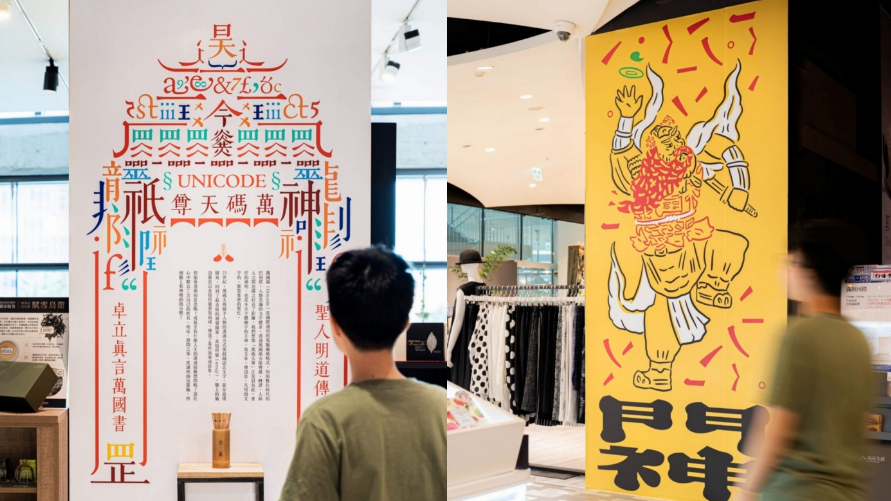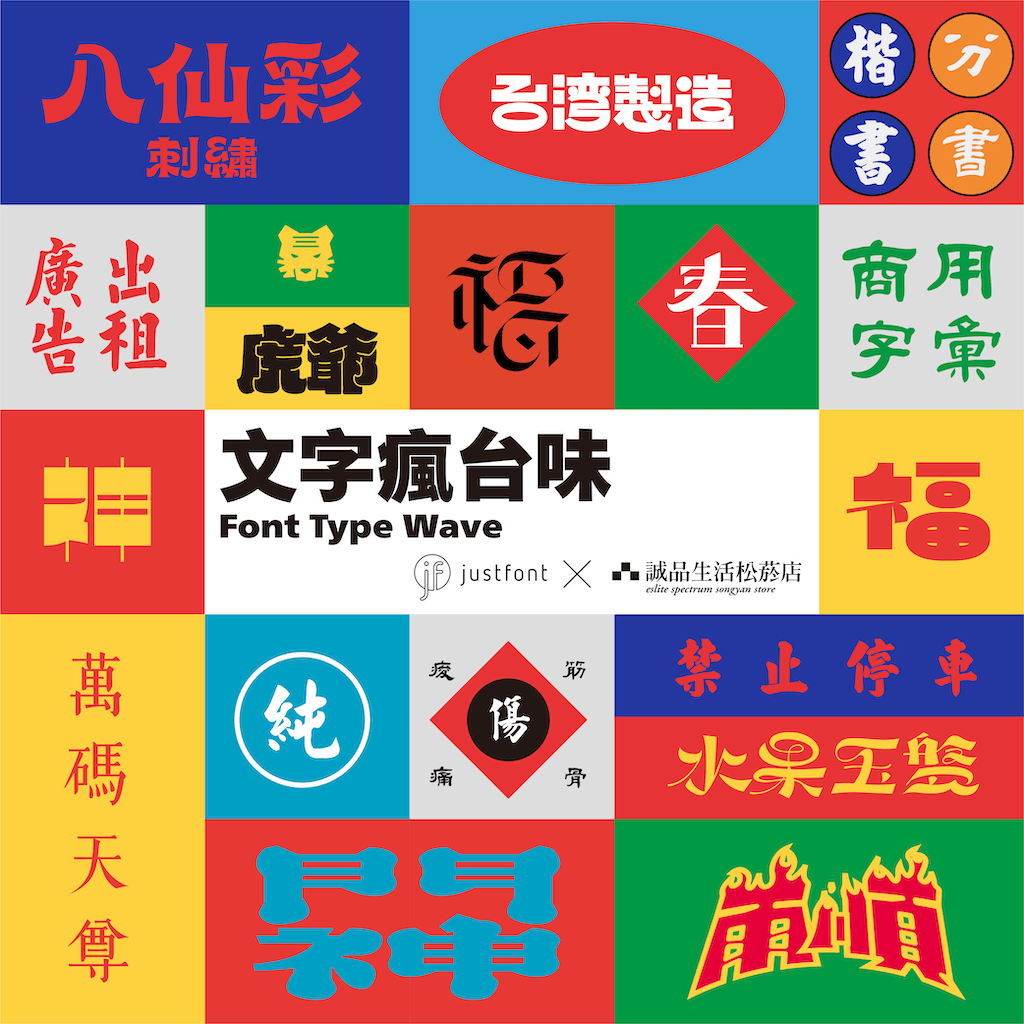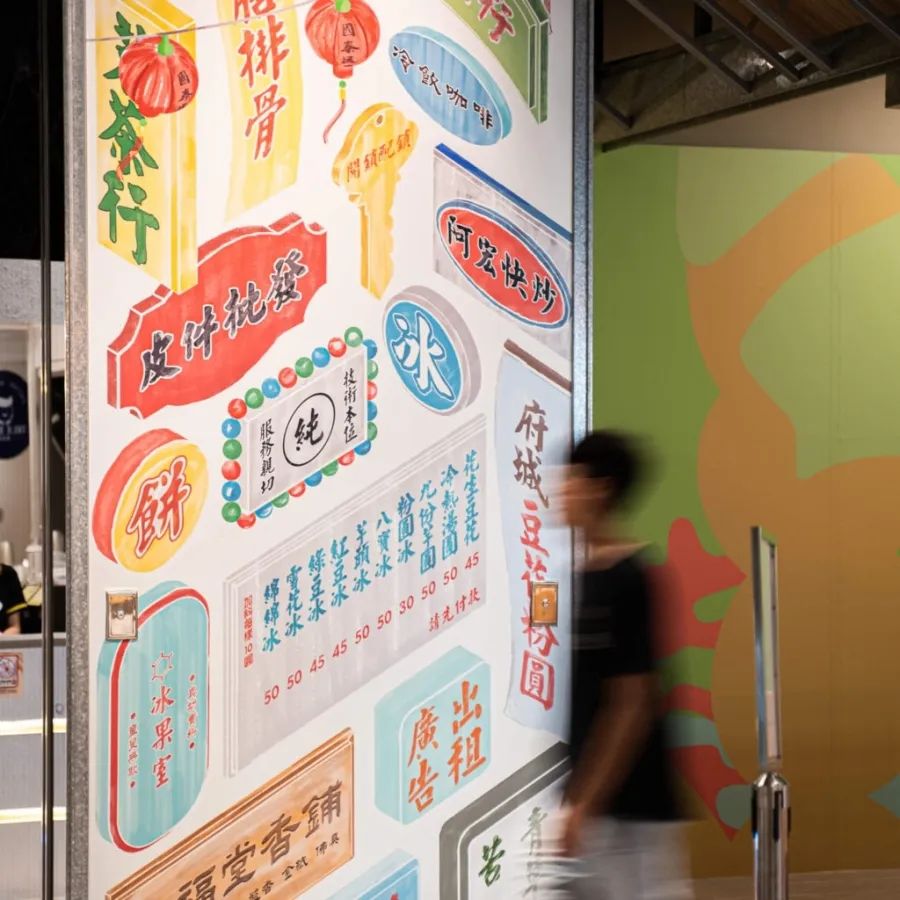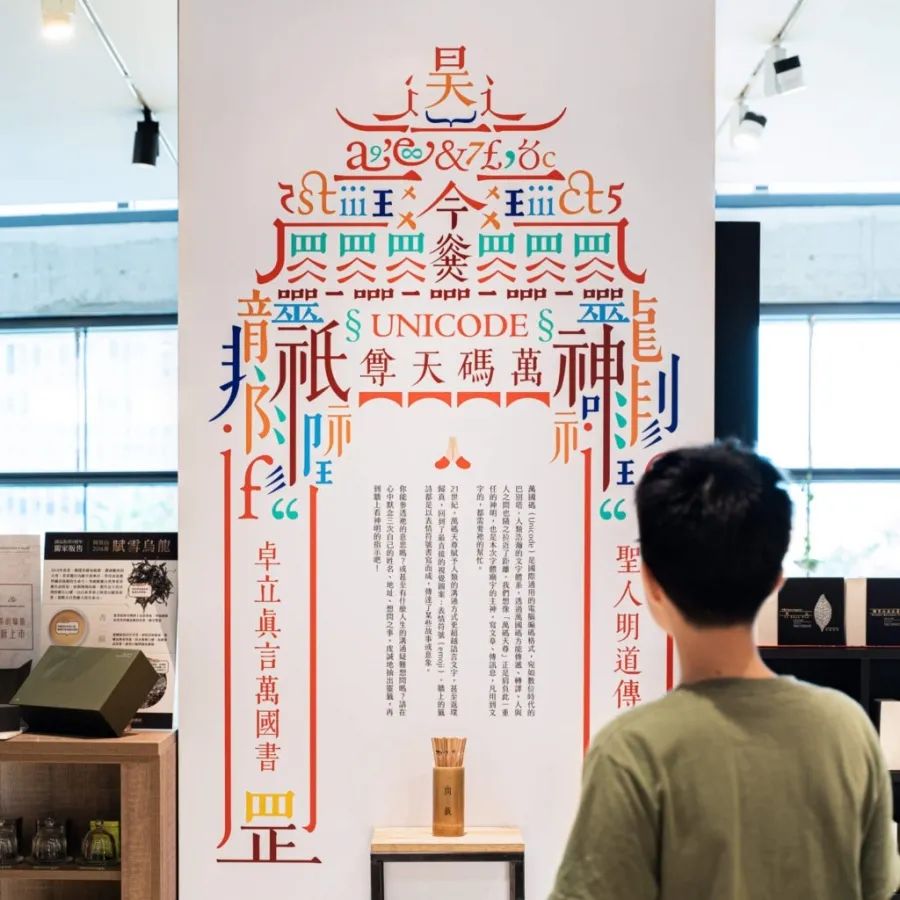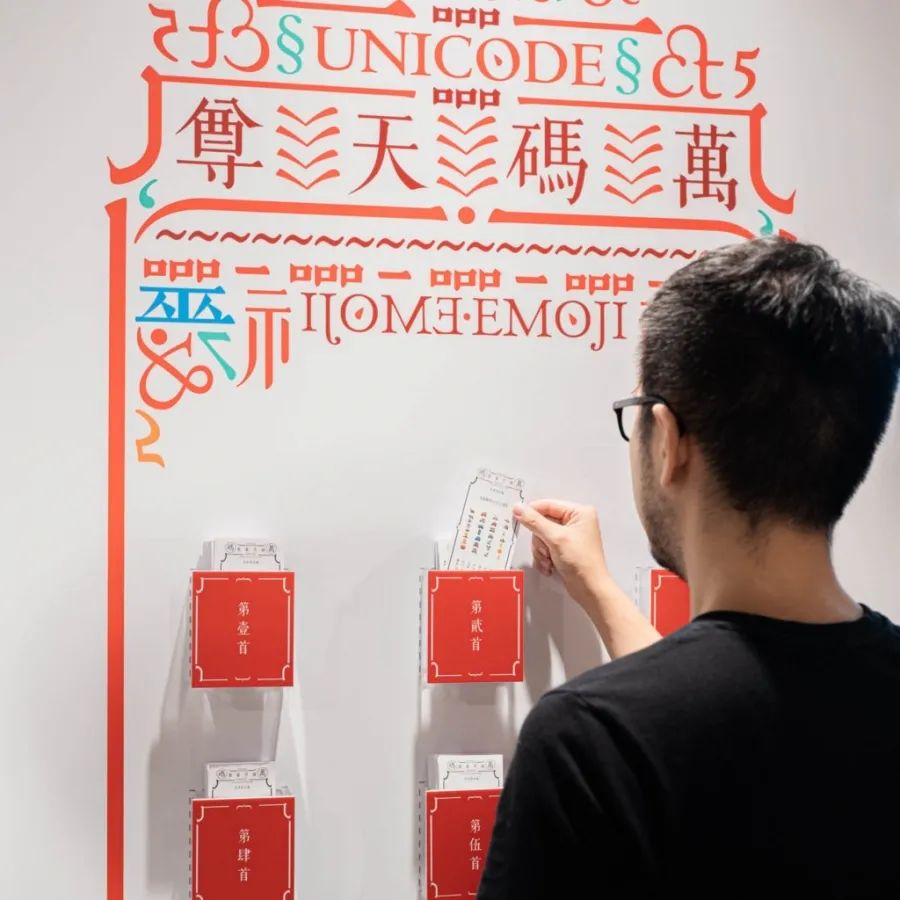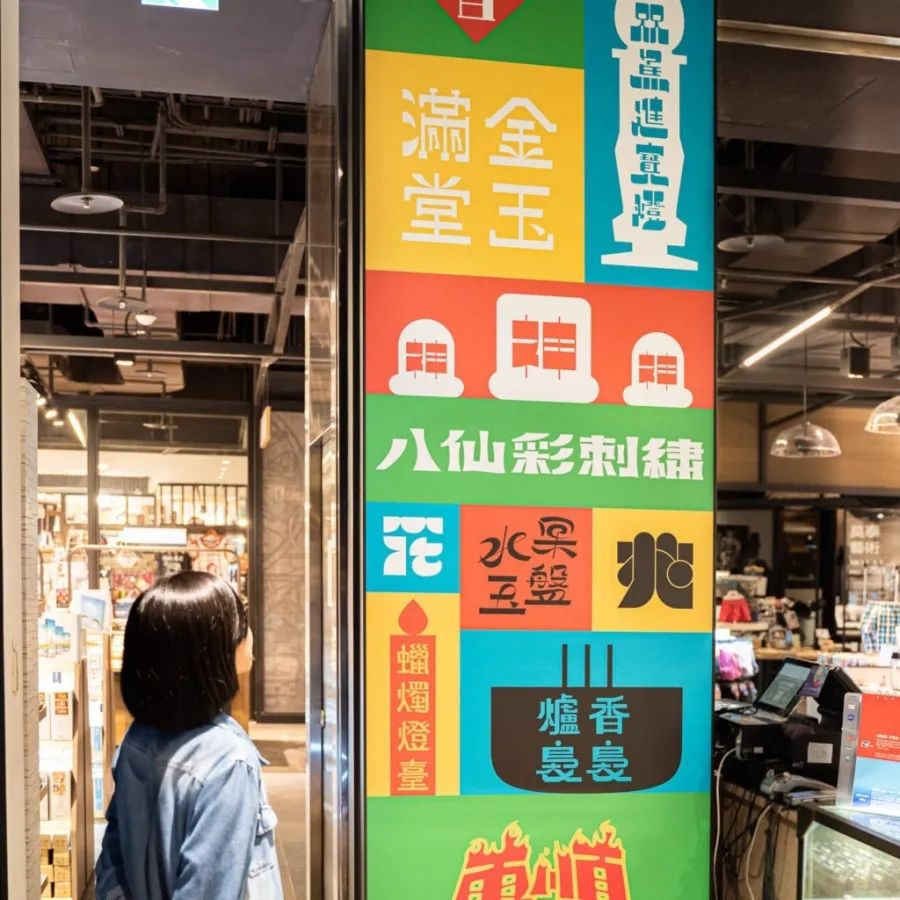
Justfont ╳ 诚品生活 | 将书店变成一座「字体庙宇」
justfont以「文字疯台味」为主题,将诚品生活松菸店打造成了一座「字体庙宇」,从B1美食街到3楼诚品书店,每一层都能看到迷人的台味字体设计!
诚品生活松菸店今年夏天祭出「台味季—翻转台味的7+2个松菸特别企划」,新世代中文字体设计团队justfont也参与其中。justfont以「文字疯台味」为主题,将诚品生活松菸店打造成了一座「字体庙宇」,从B1美食街到3楼诚品书店,每一层都能看到迷人的台味字体设计,展期就到9月15日!
B1|最好吃的字体,最熟悉的陌生人:刘体楷书
台湾街道上不少的小吃摊,是品尝台湾字体美学的必去之处;而在不少的小吃摊招牌字体中,「刘体楷书」可说是台湾街景中最熟悉的陌生人。
「刘体楷书」见字即见美味飘香,是一款常见于餐厅、夜市、小吃摊,令人食指大动的字体。这款台湾随处可见的楷书字体出于刘元祥先生于 1970 年代书写,交由文史哲出版社付梓的《商用字汇》。这系列字体参考书籍广受招牌业者欢迎,遂渐渐成为台湾街道上最常见的字体。
过去你或许不曾仔细留意,但只要「刘体楷书」出现在眼前时,记忆就会被唤醒。下回到夜市或是家裡附近的小吃摊时别忘了多留心一下,或许你就会找到刘体楷书的身影。
1F|字体门神迎庆典
门神是中国住宅和佛教道教寺庙大门处的神像,也是台湾传统文化艺术的展现。justfont特别邀请擅长平面设计与插画整合的设计师宋政杰一同脑力激荡,将门神文化揉合进字体设计中。展出期间,你将会在松菸诚品 1F 发现两尊结合独特字体元素的「字体门神」,揭开这场夏日文字庆典的序幕。
2F|供桌上的美字:包装与美术字
供桌上,十八般武艺制作的器具盛装各式点心食品。酬神的心意,五花八门,目不暇给。琳琅满目的除了色彩与气味外,字体也能带来浓烈的印象。
这种为了特殊用途、情境所设计的字体,称为「美术字」或「标准字」。与电脑打字的「字型」不同,不太需要顾及各种排版的词面抽换,美术字通常只需要做几个字就好,且能更自由地挥洒,甚至变成各种奇形怪状的样子。
业者会委託设计师制作一款美术字。比起电脑的字型,通常有更大的空间能彰显自己商品的特殊性,直观看上去也会觉得更缤纷、更有创意。
3F|绘符灵签祝愿平安:向「万码天尊」问事
万国码(Unicode)是国际通用的电脑编码格式,宛如数位时代巴别塔。藉由万国码,讯息能传递、转译,人与人之间也随之拉近了距离。
Justfont团队想像「万码天尊」是肩负此一重任的神明,也是这次字体庙宇的主神。21 世纪,万码天尊赋予人类的沟通方式更超越语言文字,甚至返璞归真,回到了最直接的视觉图案:表情符号(emoji)。牆上的签诗都是以表情符号书写而成,传达了某些故事或意象。